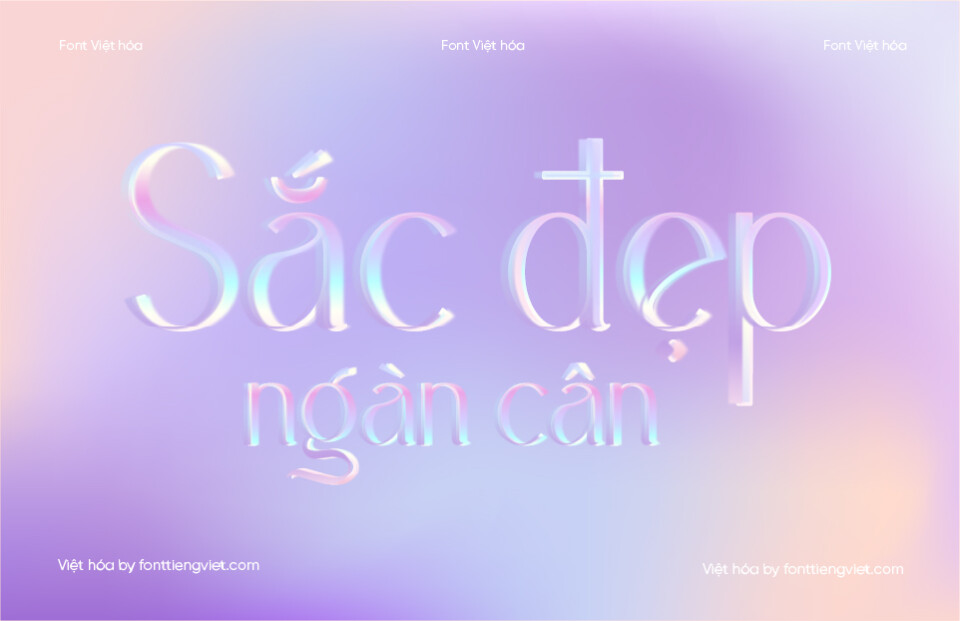
Font Việt hóa 1FTV VIP Callingstone – Font spa làm đẹp
Font Việt hóa 1FTV VIP Callingstone – Font spa làm đẹp sang trọng và đẳng cấp
Giới thiệu về Font Việt hóa 1FTV VIP Callingstone – Font spa làm đẹp
Trong thế giới thiết kế đồ họa hiện đại, việc lựa chọn một bộ Font Miễn Phí chất lượng đóng vai trò sống còn trong việc định hình thương hiệu. Font Việt hóa 1FTV VIP Callingstone – Font spa làm đẹp là một minh chứng điển hình cho sự kết hợp hoàn mỹ giữa nét vẽ thanh thoát và cấu trúc hiện đại. Được phát triển để phục vụ riêng cho phân khúc cao cấp, bộ font này mang đến hơi thở của sự tinh tế, rất phù hợp cho các không gian nghỉ dưỡng, chăm sóc sắc đẹp và các nhãn hàng thời trang. Đặc điểm nổi bật nhất của bộ chữ này chính là các đường nét uốn lượn mềm mại nhưng vẫn giữ được độ sắc nét cần thiết, giúp thông điệp truyền tải trở nên cuốn hút và dễ dàng chạm đến cảm xúc của khách hàng ngay từ cái nhìn đầu tiên.
Tại sao Font Việt hóa 1FTV VIP Callingstone – Font spa làm đẹp lại được ưa chuộng?
Thiết kế tối ưu cho ngành thẩm mỹ
Đúng như tên gọi, Font Việt hóa 1FTV VIP Callingstone – Font spa làm đẹp được sinh ra để dành cho các spa, salon tóc và viện thẩm mỹ. Font chữ này sở hữu các ký tự có độ tương phản cao giữa nét thanh và nét đậm, tạo ra hiệu ứng thị giác cực kỳ sang trọng. Khi ứng dụng lên các bảng hiệu hoặc menu dịch vụ, nó giúp nâng tầm giá trị thương hiệu, làm cho khách hàng cảm nhận được sự chuyên nghiệp và tận tâm của đơn vị cung cấp dịch vụ. Sự thanh lịch của Callingstone không hề gây rối mắt mà ngược lại, nó tạo ra một khoảng không gian thiết kế thoáng đãng và dễ chịu.
Khả năng hiển thị đa dụng trên nhiều nền tảng
Không chỉ giới hạn trong các ấn phẩm in ấn truyền thống, Font Việt hóa 1FTV VIP Callingstone – Font spa làm đẹp còn hoạt động cực kỳ mượt mà trên các nền tảng kỹ thuật số. Cho dù bạn đang thiết kế ảnh bìa Facebook, bài đăng Instagram hay giao diện website cho một thẩm mỹ viện, bộ font này vẫn đảm bảo tính đọc hiểu cực tốt. Sự linh hoạt trong việc tương thích với các phần mềm thiết kế phổ biến như Photoshop, Illustrator hay Canva giúp các nhà sáng tạo nội dung tiết kiệm được rất nhiều thời gian trong quá trình sản xuất hình ảnh. Độ chỉn chu trong từng glyph của font giúp việc sắp xếp bố cục trở nên hài hòa và đồng nhất hơn bao giờ hết.
Cách ứng dụng Font Việt hóa 1FTV VIP Callingstone – Font spa làm đẹp vào thực tế
Thiết kế bộ nhận diện thương hiệu cao cấp
Việc sử dụng Font Việt hóa 1FTV VIP Callingstone – Font spa làm đẹp cho logo và tagline là một bước đi thông minh. Bạn có thể kết hợp nó với các tông màu pastel như hồng phấn, vàng hồng hoặc trắng sứ để tạo ra một phong cách tối giản mà thượng lưu. Ngoài ra, việc tận dụng các ký tự thay thế (alternates) trong bộ font này sẽ giúp các nhà thiết kế tạo ra những biến thể chữ độc đáo, tránh được sự rập khuôn và làm nổi bật cá tính riêng của từng cơ sở spa. Đây là yếu tố then chốt giúp khách hàng ghi nhớ thương hiệu của bạn lâu hơn trong tâm trí giữa vô vàn đối thủ cạnh tranh hiện nay.
Lời kết về bộ font đẳng cấp này